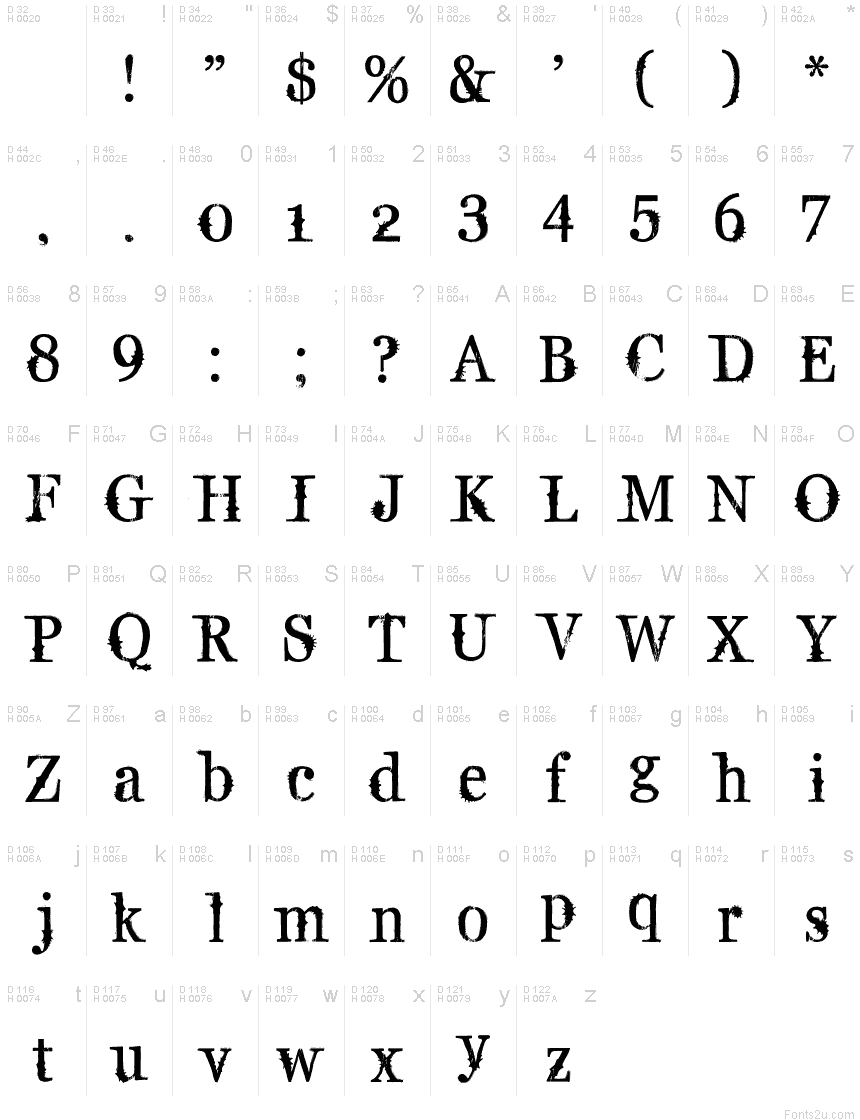
Supafly 36, stworzony przez Gyomsegs, to darmowy, postarzany krój typu display o surowym, poszarpanym charakterze – w połowie przypominający wiktoriańskie plakaty, a w połowie relikt starej drukarni. Litery łączą wysokie, klasyczne formy z postrzępionymi krawędziami i nieregularnymi wykruszeniami, co nadaje sylwetce żywego, nieokrzesanego wyrazu.
Świetnie sprawdzi się na ulotkach muzycznych, grafikach na Halloween, okładkach zinów, etykietach i nagłówkach, gdzie nuta brudu pomaga zbudować odpowiedni klimat. Jako darmowy font, doskonale nadaje się też do krótkich tytułów, szkiców logo i inicjałów, ponieważ jego poszarpane kontury i nietuzinkowe kształty od razu przykuwają uwagę.